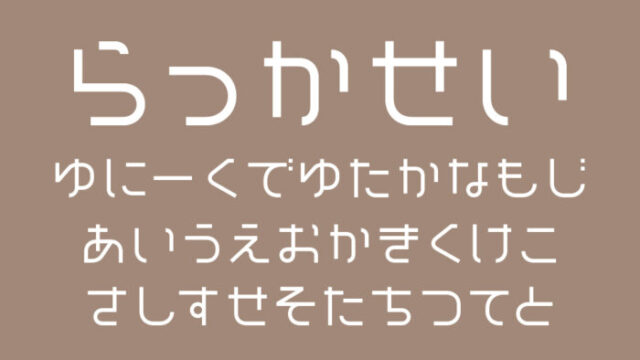
今回は、「かわいい!」と声が出そうな、ポップでキュートな日本語フリーフォントをご紹介します。
ころんとした丸み、リズミカルでちょっとハズした文字感、手描き風の温かみなど、そんな遊び心いっぱいのフォントは、デザインやグッズ制作、ゆるくて楽しいイベントのビジュアルなどにぴったりです。もちろんSNS用画像やYouTubeのテロップ、ネームロゴにも活躍してくれるはず!
今回は、明るくて元気、だけどどこか素朴でやさしさも感じられる、ポップでキュートな日本語フリーフォントをピックアップしました。にぎやかで楽しい世界観を表現したいときに、ぜひ取り入れてみてください。
ポップでかわいい日本語フリーフォントのまとめ
以下のサンプル画像は本記事で紹介している一部ですが、文字だけでもポップで可愛らしいフォントをご紹介しています。
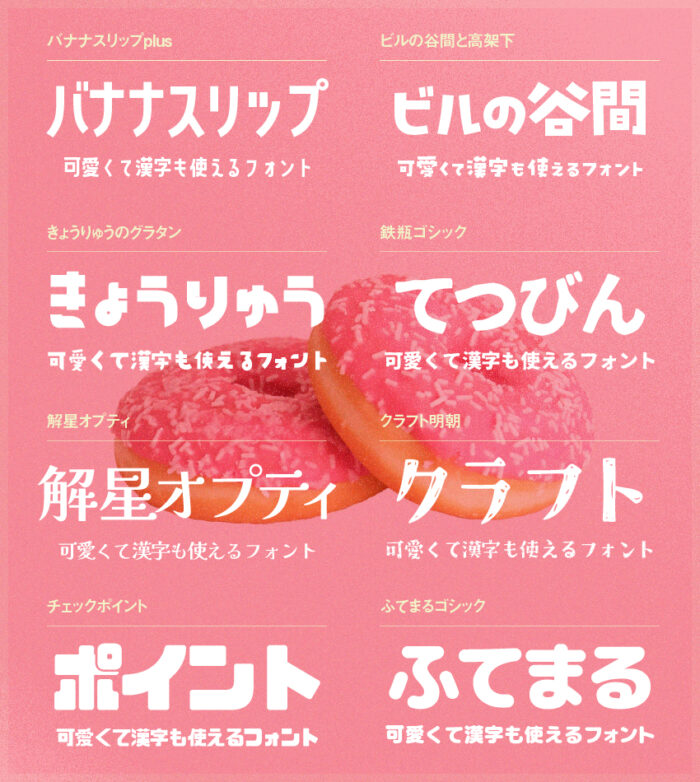
フォント事例画像の中にスペースが開いている部分は、フォントに文字が含まれていない部分になりますので、ご了承ください。
こども丸ゴシック
こども丸ゴシックフォントは、こどもが書いたような可愛らしい文字と、文字の輪郭がモコモコしており、インクのにじみのような、クレヨン書いたような質感がまたGOODです。
バナナスリップ
バナナスリップフォントは、堅苦しくはしたくないし、可愛すぎるのもちょっと違う、みたいなシーンのときにはピッタリなフォントです。
自分のまわりの人もバナナスリップをよく使っているのを見かけたり、デザイナーや動画編集者からとっても人気のフリーフォントです。とってもかわいいので、バナーやYoutubeのサムネなどでよく使用されているのを見かけます。このクオリティのフォントがフリーなのがすごい!
ビルの谷間と高架下フォントは、漢字とひらがな、カタカナのでこぼこ感が可愛いらしいデザインフォントです。
統一しすぎない字形のデザインがポップでかわいいらしいフォントです。あえて漢字とかな文字のサイズ感を統一していないように作られており、でこぼこしている様子もとっても可愛いです。
キウイ丸(Kiwi Maru)
キウイ丸フォントは、手書き風と丸ゴシックの中間のような形をしているフォントです。そのため、女性向けや子供向けなど優しくてかわいいデザインとの相性はとっても良いフォントです!
フォントの太さ(ウェイト)も300(Light)、400(Regular)、500(Medium)の3種と豊富なので、タイトルや本文・テロップなど使い分けることができます。
クラフト明朝
クラフト明朝フォントは、手書きのようなグシャグシャと塗りつぶした雰囲気やクラフト感あるかすれ加工が施されているユニークなデザイン系明朝フォントです。
柔らかい印象がありますが、明朝体がベースになっているので、幼稚な印象になりすぎない程度に子供っぽい遊び心があるフォントです。子供向けはもちろんですが、ポップなデザインとも相性が良さそうです。めっちゃカワイイー!
プイッコ
プイッコは、文字の向きや文字の形がランダムな動きをしていることで、コロッとした可愛さがあるデザインフォントです。
推しゴは、推し活で使うことを目的として制作されたデザインフォントです。推し活うちわやグッズ制作で活躍すること間違いない可愛らしいフォントです。
ステッキ(Stick)
ステッキフォントは、直線的な棒で構成されている文字ですが、無機質な直線的が逆に、躍動感・動きがあるデザインになっていフォントです。
元気な子供っぽい雰囲気で、ポップなデザインとの相性はとても良く、見出しやキャッチコピーなどに使用すると良いですね!
つなぎゴシック
つなぎゴシックフォントは、角を丸く加工し、墨だまり処理を加えられたゴシック体のフォント。
角丸加工が柔らかな印象をあたえ、こぶりなひらがな・カタカナのデザインも柔らかく優しい雰囲気をもたせているフォントです。
きょうりゅうのグラタン
きょうりゅうのグラタンフォントは、コロコロとした可愛いらしいフォルムがクセになるフォントです。いい意味でクセのある文字なので、見出しやタイトルなどに使うも良し!Youtubeのサムネなどに使って目立つタイトルになりそうです。
デザインに取り入れるだけで、十分にインパクト目を引くバナー・アイキャッチ・サムネなどのデザインが作れそうです。
りいクッキー
りいクッキーフォントは、角がカクカクしており、ラインが太めで手書き感あるコロコロとした可愛らしいフォルムが特徴的なフォントです。
見ているだけで楽しめる元気いっぱいの楽しい気持ちになれるフォントになっています!
けいふぉんと!フォントは、アニメのロゴをモチーフに作成されたフォントなので、とってもポップで可愛らしいフォントになっています。動画編集者には人気のフォントの1つです。
アニメロゴで使われたタイプに似せているため、とってもカワイイフォルムで、同人アニメや動画のアイキャッチなどに使うとインパクトやデザイン性が出そうで素敵ですね。
あかずきんポップ
あかずきんポップフォントは軽やかで弾むような、楽しい雰囲気のキュートなポップさを感じることができるフォントです。
文字に勢いや動きを感じるので、アニメ・マンガ・ゲーム系の動画テロップや、バナーデザインとの相性はバッチリです!
はちまるポップ(Hachi Maru Pop)
はちまるポップフォントは、80年代頃に流行した丸文字にインスパイアされて、現代風にアレンジされたデザインの丸文字系フォントです。
80〜90年代の少女向けマンガなどに使われていそうな丸みがポップな印象がありとっても可愛らしい文字になっています。現代風にアレンジされていますが、レトロな印象もありますね。
きんいろサンセリフ
きんいろサンセリフフォントは、人気アニメのタイトルロゴをモチーフとしているフォントなので、他にはないユニークなフォルムがポップでかわいい印象がでるので、同人誌のタイトルロゴデザインに取り入れても面白いかもしれません。
Youtubeのサムネイルやテロップでよく使用されているフォントの1つです。
キルゴUフォントは、ゴツゴツしたフォルムがポップでドンっとしている強め印象になるので、バナーや動画アイキャッチなどのタイトルやキャッチコピーに使うとインパクトがでること間違いなし!
こちらもYoutubeのサムネイル画像やテロップなどでよく利用されているフォントの1つです。
まっつん丸のあたまでっかちフォント
あたまでっかちフォントは、あたま(上のほう)は大きく、おしり(下のほう)はすぼんだような、ちょっとかわいらしい頭でっかちな少しユニークなフォルムのデザインフォントです。
丸みがあり可愛らしいフォルムと、インパクトがあるので、アイキャッチなどのタイトルとして使ってみるといいかもしれません!収録漢字は少し少なめですが、他のフォントと合成フォントして作ればOK!
いかほ
いかほフォントは、某ゲーム内で使用されているフォントにも似ていることもあり、某ゲームの実況動画などでもとっても人気のあるフォントの1つです。
デザインがカワイイので、もちろん某ゲーム関連以外のデザインなどでも使えるフォントです。
ラインが極太ですが、文字先が先細っていくフォルムは可愛くもあり、インパクトもあるフォントになっています。かわいい!
ぽめらにあんフォント
ぽめらにあんフォントは、ネーミングから連想できるようにワンちゃんのポメラニアンのようなモコモコでコロッとしているフォルムがとっても可愛らしいフォントになっています!
ゆるくてカワイイ、女性向けデザインや子供向けデザインと相性がとっても良さそうです。
しろくまフォント
しろくまフォントは、線幅がランダムに太かったり細かったり、フォルムがとっても可愛く、少し手書き感のあるラフなフォルムは他にはない独特な雰囲気をもつフォントです。
ふわふで
ふわふでフォント、墨で書いたような滲み感が墨田まりの質感ありとても渋いですが、文字のフォルムがまるっとしていてふわふわな可愛いデザインになっています。手書き+女性+墨文字という以外な組み合わせの珍しいフォントとなっています。
他のフォントにはない質感と可愛さを併せ持ったとってもキュートなフォントです。
チルアウト
| 漢字 | ✕ |
チルアウトフォントは、幅がそれぞれ違い、ゆるい印象があるのでエモくてチルくてかわいいフォントです。
特徴的な手書き感がカワイイ&カッコいいので、エモい写真と組み合わせてキャッチコピーやタイトルに使うと、すごくGOODでCHILLな雰囲気を出せます。
油性マジック(Yusei Magic)
油性マジック(Yusei Magic)フォントは、角を丸く加工し、墨だまり処理を加えられたゴシック体のフォント。
角丸加工が柔らかな印象をあたえ、こぶりなひらがな・カタカナのデザインも柔らかく優しい雰囲気をもたせているフォントです。
「つなぎゴシック」フォントのページ
うたミンフォント
うたミンフォントは、「歌う文字」をコンセプトに音符のようなエレメントが文字の先端に装飾されているのが音が聞こえてくるかのような文字に感じます。可愛らしさもありますが、少しエレガントで高貴な雰囲気もあります。
ふんわりラウンド
| 漢字 | ✕ |
ふんわりラウンドフォントは、やや手描きふうの骨格で、丸ゴシックのような、太めの先端丸の線のベースのフォントになっています。カワイイー!!
大人っぽい美しくも可憐な文字がとっても素敵なフォントです。
にくまるフォントは、ユルくて、適当具合が柔らかい雰囲気が特徴のフォントです。
子豚さんのようなマルマルっと太ったフォルムは愛らしく可愛らしいデザインになっています。
KFひま字キッズ
KFひま字キッズは、元気な子供たちをイメージされて作られてたポップでかわいいフォントです。飛び跳ねているような動きがある文字となっていて可愛いです。
漢字の収録がないフォントなので、他フォントと混色で使うのがおすすめです。
解星オプティ
解星オプティフォントは、文字先に付いているドットの丸い装飾が可愛らしいモダンな印象の明朝体フォントです。
でらすこゴシック
でらすこゴシックフォントは、極太系ゴシックでインパクトのあるフォントです。ちょっとクセのあるゴシックのデザインなのが可愛いポイントです。